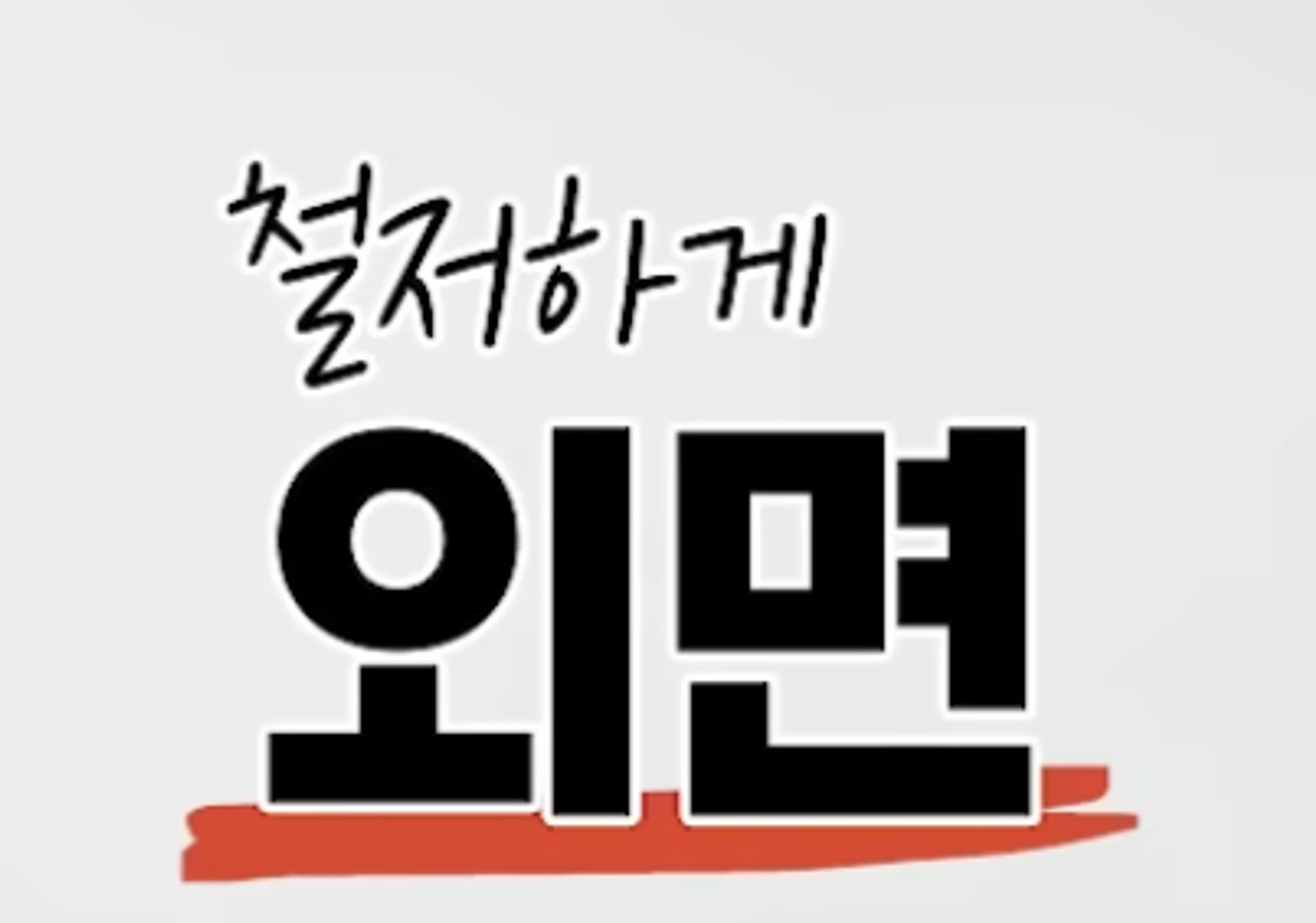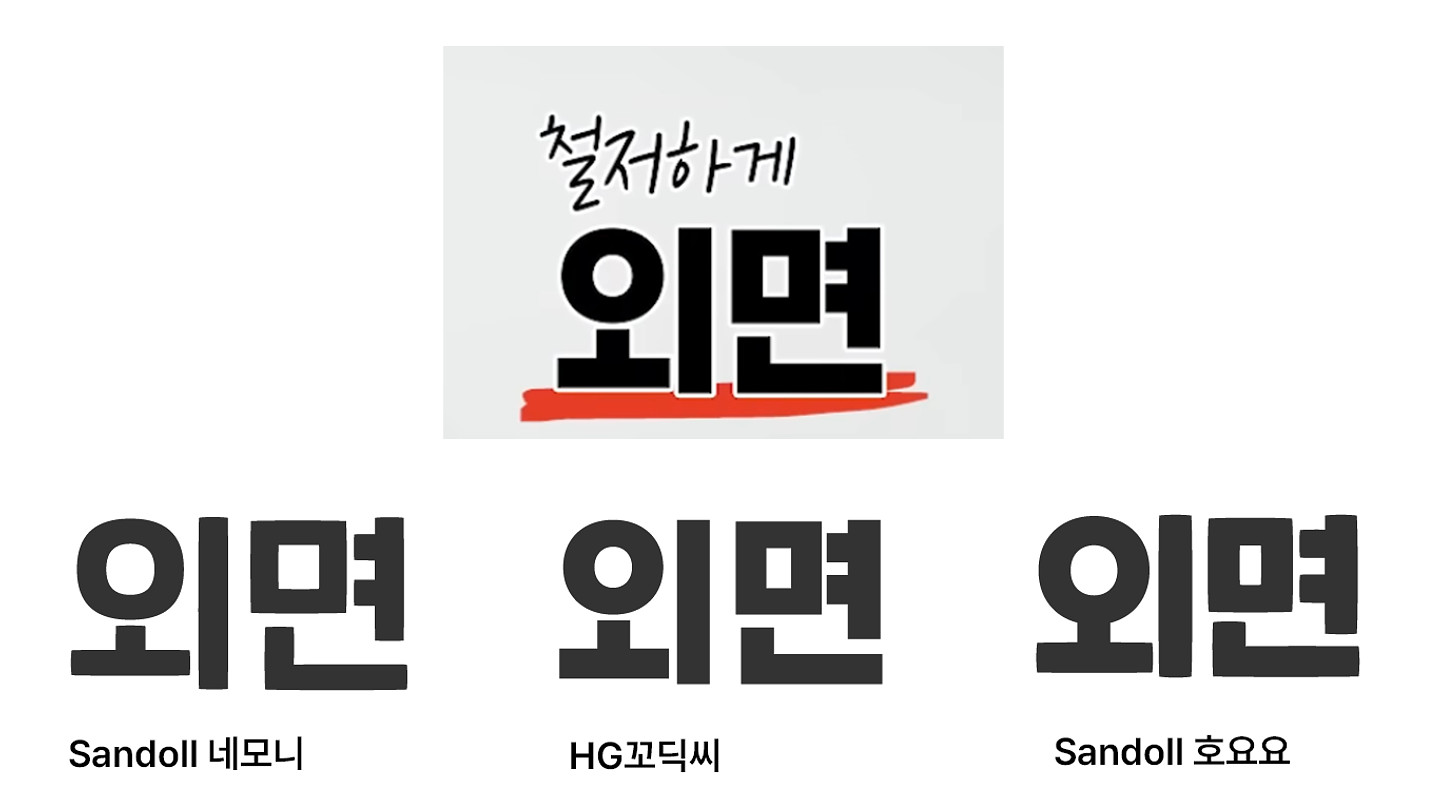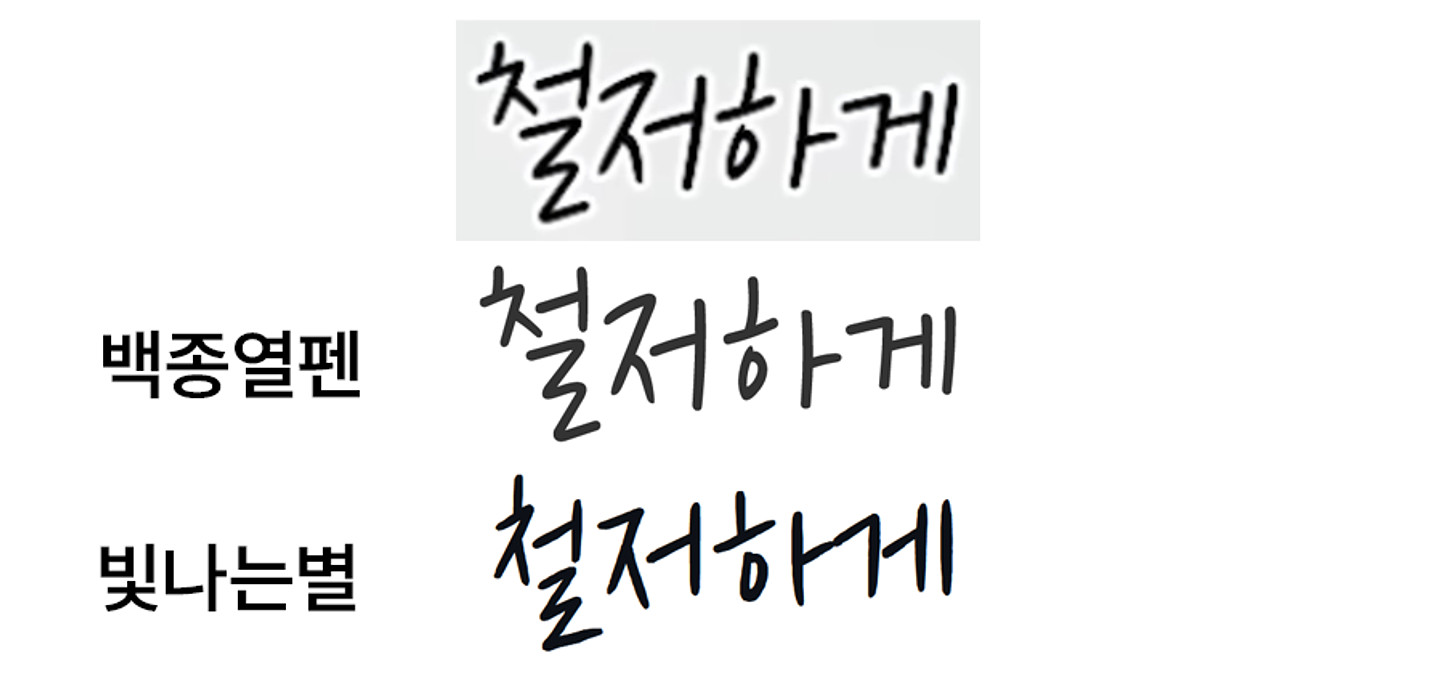
공병각,네모니
산돌에 있는 공병각 폰트랑 네모니 폰트네요
HG꼬딕씨
하단 폰트입니다. 네모니, 호요요 아닙니다. 이 이미지의 가운데가 꼬딕씨, 좌측이 네모니, 우측이 호요요입니다.
Sandoll 백종열펜
상단 폰트입니다. 백종열펜에 기울기 적용한 것이고 공병각, 빛나는별은 아닙니다.
카페24 빛나는별, Sandoll 호요요
위에는 카페24 빛나는별 아래는 Sandoll 호요요체 입니다. 저가 틀릴수도 있어요. Sandoll 네모니 일 수도 있습니다. 꼬딕씨는 아닙니다.